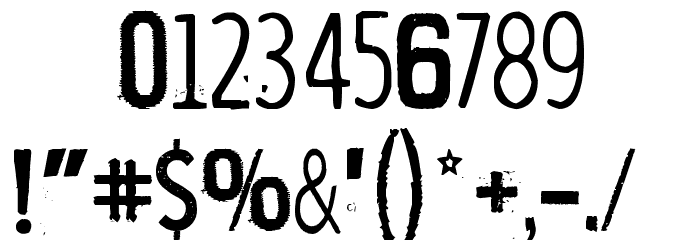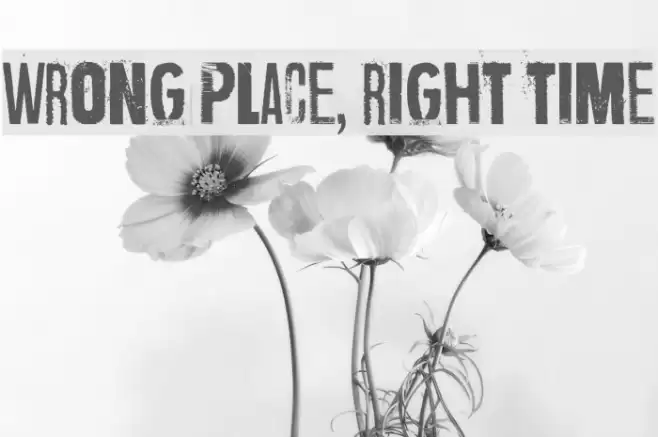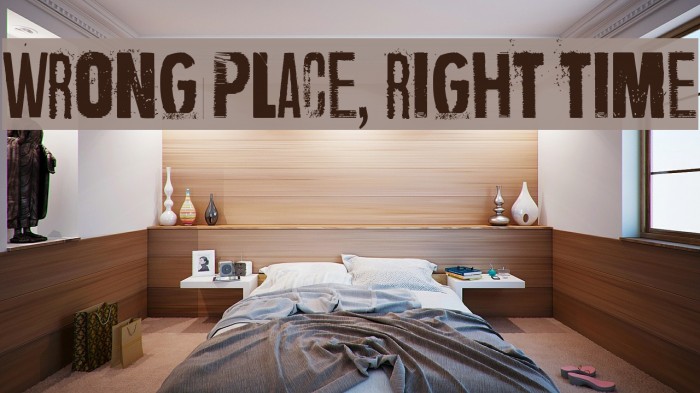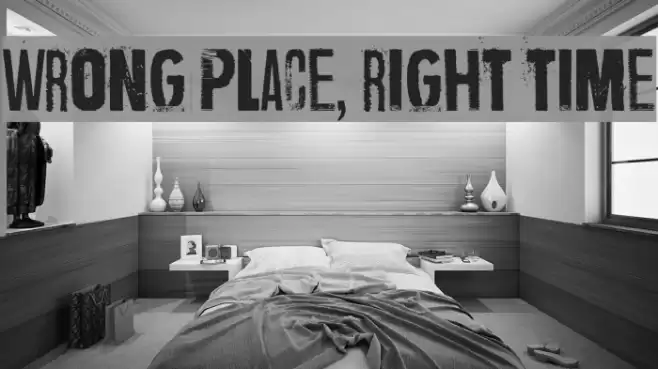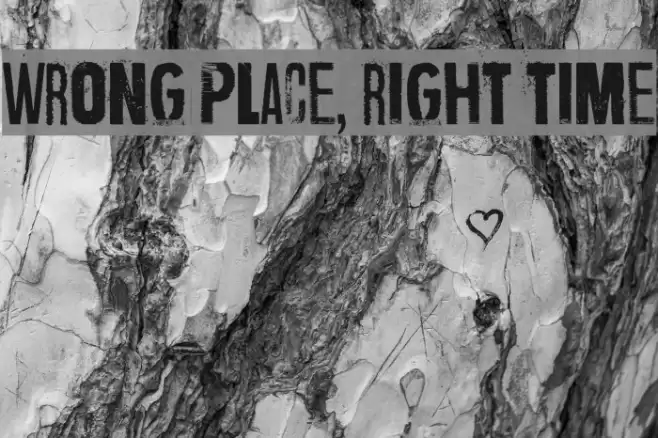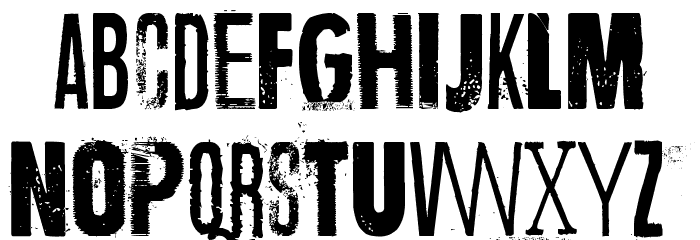
Wrong place, right time Font
| النمط العام | Vintage, Industrial |
| مشاريع مقترحة | Ideal for posters, album covers, branding for edgy or urban-themed products, and any design needing a strong, textured typeface. |